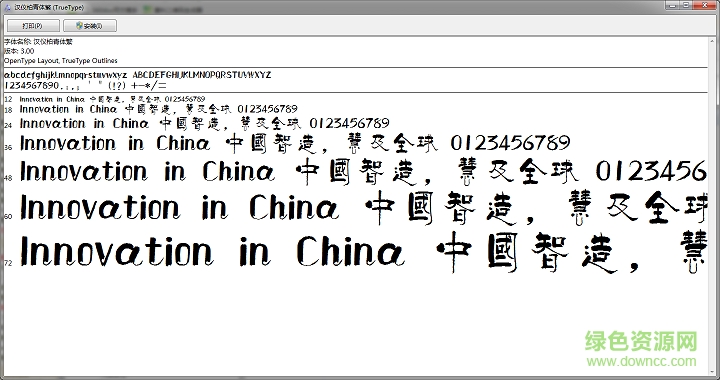
hyj4gf
hyj4gf字體是一款根據(jù)柏青先生的書法打造的毛筆字體,充分的吸收了作者書法的特色,字形多變且富有美感,有喜歡書法字體的朋友歡迎下載使用!
hyj4gf字體簡(jiǎn)介
hyj4gf是什么字體?就是我們常說的漢儀柏青體繁體字體,是一款非常有特色的繁體中文字體,這款字體看上去會(huì)讓你覺得上粗下細(xì),左寬右窄,并且每個(gè)字收筆的筆劃都非常有趣!